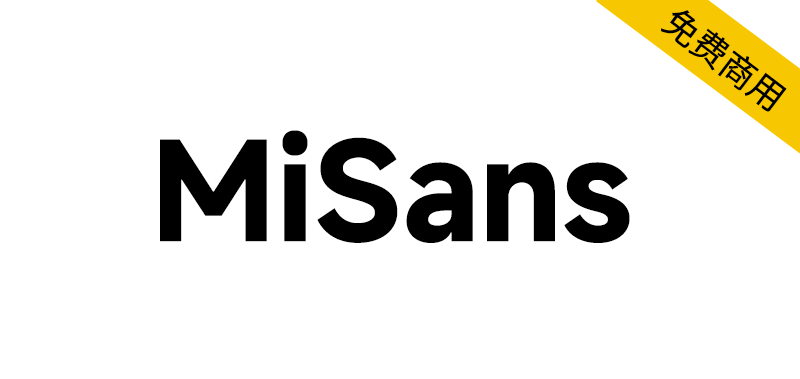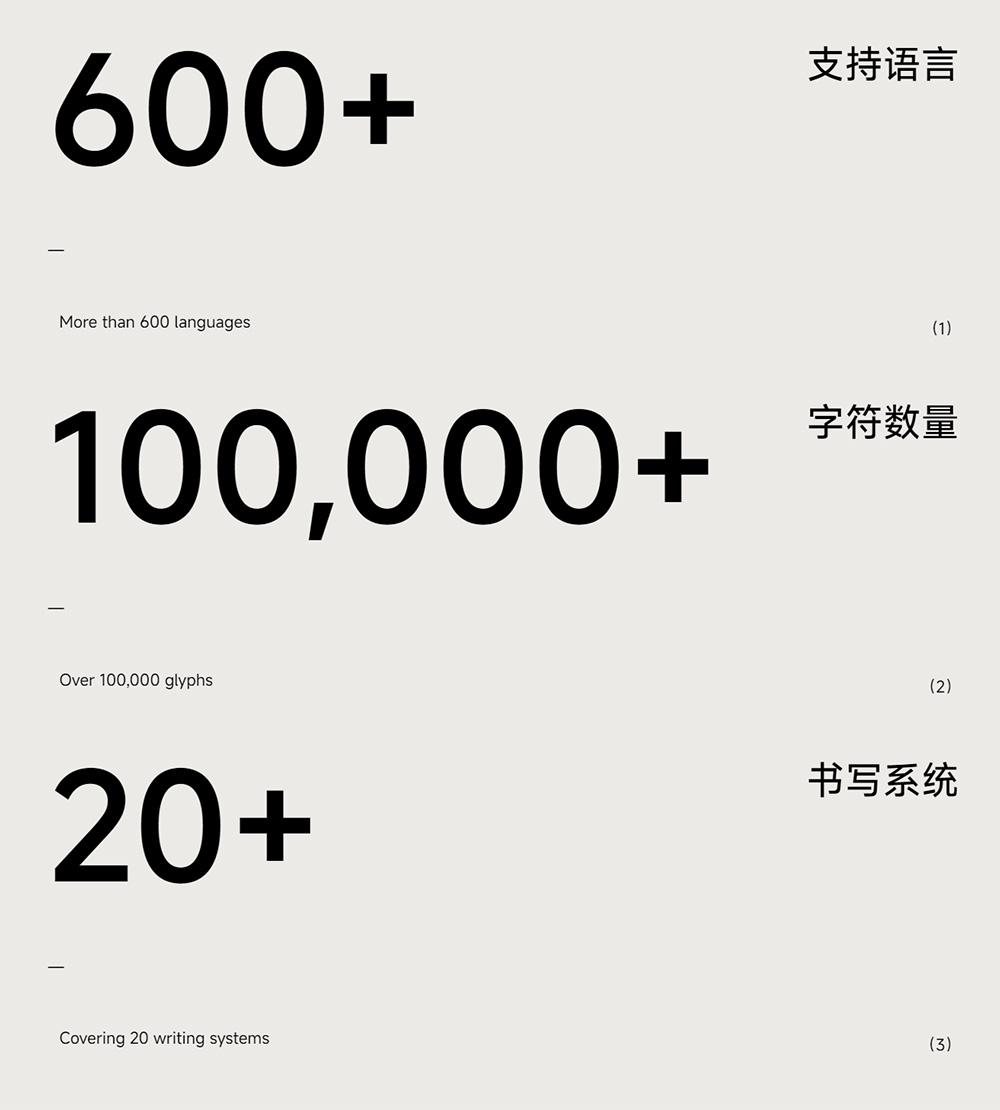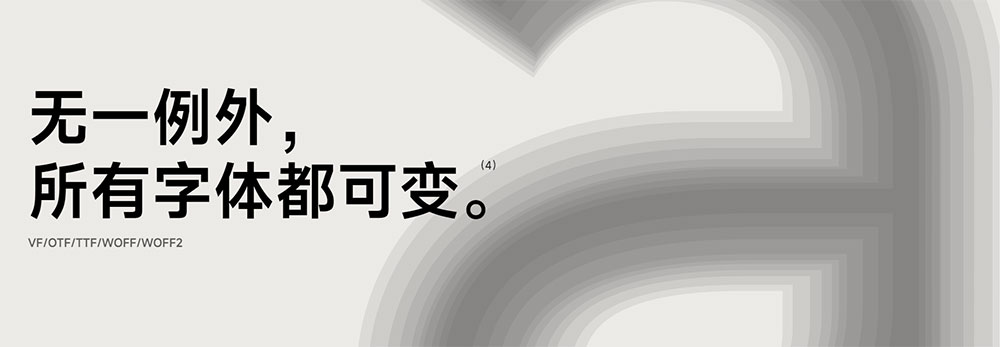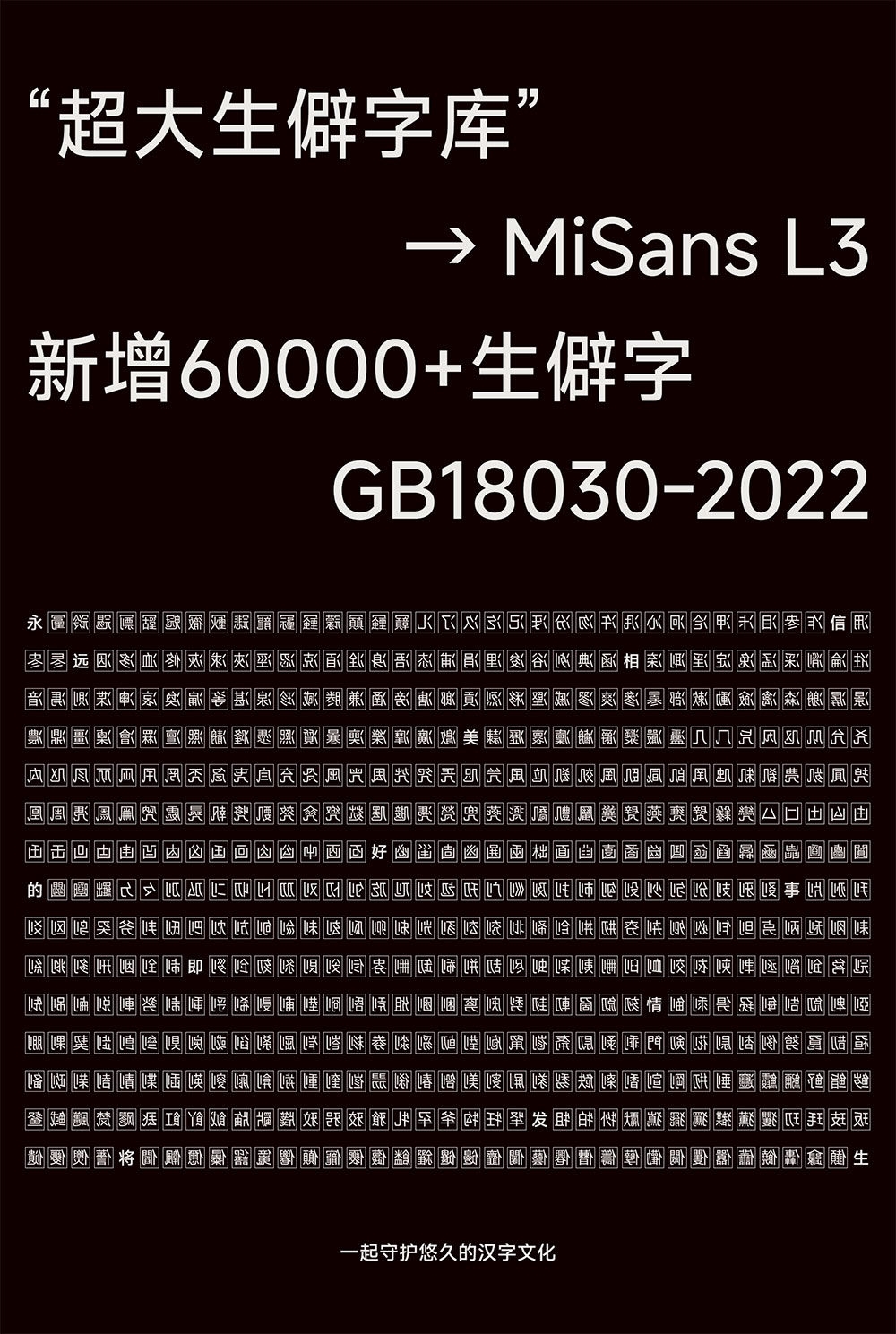
2021 年在 MIUI 13 中推出全新系统字体 MiSans;字体规格、细节全方位升级并加入了丰富的 OpenType Features,并在发布当天宣布该字体面向全社会免费商用。
2023 年在全新系统 Xiaomi HyperOS 中推出全球语言定制字体项目— MiSans Global。这是一个庞大的字体家族,涵盖 20 多种书写系统,支持 600 多种语言,字符数量累计超过10万个。
MiSans Global 是由小米主导,联合蒙纳字库、汉仪字库共同打造的全球语言字体定制项目。这是一个庞大的字体家族,涵盖 20 多种书写系统,支持 600 多种语言,字符数量超过 10 万个。作为 Xiaomi HyperOS 系统默认字体,我们以简约/清晰,人文/易读,统一的视觉风格为基本原则出发,构建多语言信息体验一致性,旨在帮助为 Xiaomi HyperOS 提供互联的通用体验。
超大生僻字库,MiSans L3,新增60000+生僻字,符合 GB18030-2022 最新字符集国家标准
GB18030-2022 强制规范三个实现级别,于 2023 年 8 月 1 日起开始执行。实现级别1共 27,584个汉字;实现级别 2 包含实现级别 1,此外,实现级别 2 还支持《通用规范汉字表》中的没有包含在实现级别 1 之内的编码汉字,共计 27,780 个汉字;实现级别 3 包含实现级别 2,此外,实现级别 3 还支持新标准件规定的全部汉字及表 3 中的康熙部首,总计 87,887 个汉字,用于政务服务和公共服务的产品应满足实现级别 3 的要求。 MiSans 包含级别 1+ 级别 2,MiSans L3 为级别 3 字库(该字库不包含级别 1 和级别 2)。MiSans 包含级别1+级别2,MiSans L3 为级别3字库(该字库不包含级别1和级别2)
什么是可变字体?
可变字体是 OpenType 在 1.8 版规范中引入的扩展规范,简单说明就是一个字体文件同时支持多个字体形态,可以将多个字体文件合在单个字体文件中,通过定义字体内的变化来实现单轴或多轴设计空间。
是否所有字体都支持可变?
MiSans L3 生僻字字库(GB18030-2022 级别3)仅支持 Regular 字重。 其他所有字体均支持可变。
MiSans Global 的制作分工
由小米主导,联合蒙纳、汉仪共同制作完成。其中蒙纳负责泰语、老挝及印度的所有地区语言。汉仪负责繁体中文、阿拉伯语、藏文、缅甸、高棉。